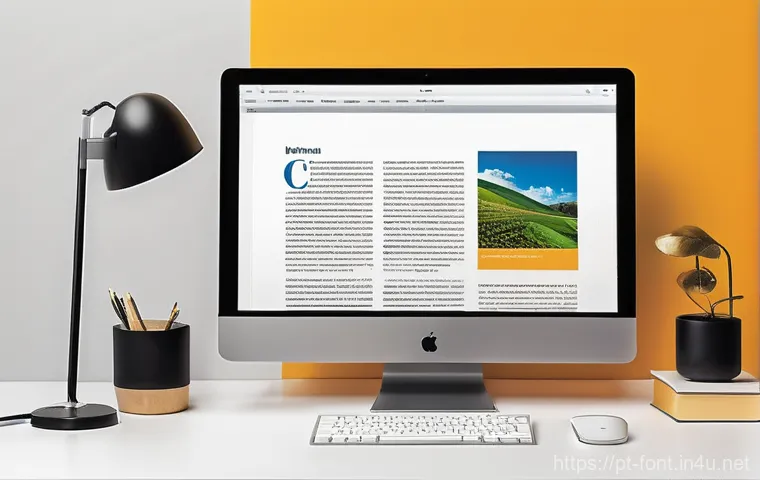
Olá, pessoal! Eu sei que o mundo das apresentações pode ser um desafio e muitas vezes focamos tanto no conteúdo que acabamos esquecendo de um detalhe que faz TODA a diferença: a escolha da fonte e o seu tamanho.
Juro pra vocês, já vi apresentações geniais perderem completamente a força porque a mensagem se perdia em meio a textos ilegíveis ou a um design que mais confundia do que ajudava.
Não é só uma questão de “bonito” ou “feio”, gente; estamos falando de impacto, de profissionalismo e, principalmente, de garantir que sua ideia brilhe de verdade!
Nesta era digital, onde reuniões online se tornaram a norma e a atenção das pessoas é um recurso valiosíssimo, o que funciona bem em um auditório lotado talvez não seja o ideal para quem está assistindo no celular ou no tablet.
As tendências de design e as ferramentas de inteligência artificial estão sempre evoluindo, mas o bom senso tipográfico continua sendo a base para prender o público.
Afinal, a primeira impressão e a legibilidade contínua são cruciais para manter sua audiência engajada do início ao fim. Querem evitar aqueles olhares confusos e ter apresentações que realmente convertem e impressionam, deixando a sua marca por onde passam?
Vamos mergulhar fundo e desvendar todos os segredos para escolher a fonte perfeita!
A Psicologia das Fontes: Mais Que Estilo, Emoção e Percepção
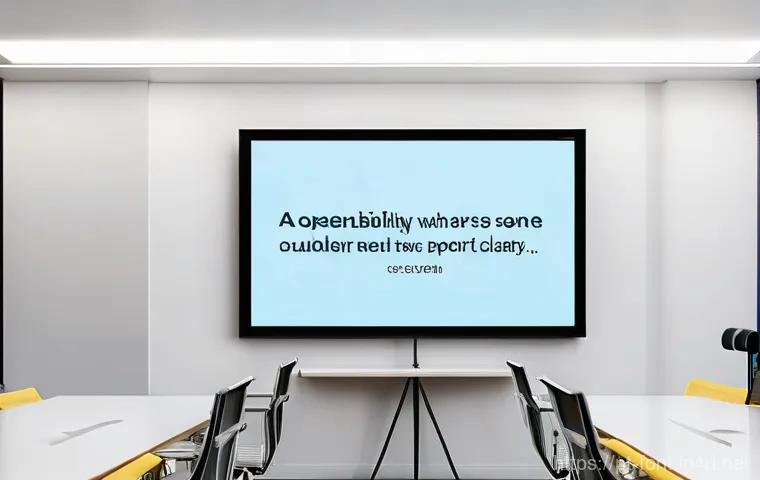
Como a Escolha da Fonte Afeta a Audiência
Sabe aquela sensação quando você vê um logotipo ou um texto e ele simplesmente “passa a mensagem” sem você nem precisar ler com atenção? É a psicologia das fontes agindo!
Acreditem, cada tipo de letra evoca uma emoção diferente, uma percepção particular. Uma fonte mais arredondada pode transmitir amigabilidade e acessibilidade, perfeita para um workshop criativo.
Já uma fonte mais serifada e clássica pode gritar “autoridade” e “tradição”, ideal para uma apresentação acadêmica ou corporativa séria. Eu mesma já testei e comprovei: em um evento sobre inovação, usei uma fonte mais moderna e limpa e a reação do público foi visivelmente mais engajada, sentindo que o conteúdo era realmente de ponta.
Se eu tivesse usado uma fonte super formal, talvez a mensagem de vanguarda não tivesse sido tão bem absorvida. É como escolher a roupa certa para a ocasião, a fonte precisa estar em sintonia com o seu discurso e com quem está do outro lado.
Pensar nisso me ajudou a transformar slides “ok” em apresentações verdadeiramente memoráveis.
Transmitindo Credibilidade e Profissionalismo
A verdade é que a credibilidade começa antes mesmo de você abrir a boca. Ela começa no visual. Uma fonte mal escolhida, que parece infantil para um tema sério, ou que é difícil de ler, pode, infelizmente, minar toda a sua autoridade.
Eu já caí nessa armadilha no início da minha carreira, usando fontes “divertidas” demais em apresentações que exigiam seriedade, e a percepção dos meus superiores não foi das melhores.
Aprendizado doloroso, mas valioso! Hoje, entendo que a fonte é uma extensão da sua voz. Ela precisa reforçar o profissionalismo e a seriedade da sua mensagem, se for o caso.
Por exemplo, fontes como Montserrat ou Lato são escolhas seguras para o ambiente corporativo, transmitindo clareza e um toque moderno sem perder a formalidade.
É sobre construir confiança visualmente, e uma tipografia bem pensada faz exatamente isso. Se você quer que as pessoas levem sua apresentação a sério, comece pela base: a escolha da fonte certa que comunica respeito pelo seu conteúdo e pela sua audiência.
Tamanho É Documento? A Importância do Tamanho da Fonte para Apresentações Impecáveis
Adequando o Tamanho para Diferentes Ambientes
A grande questão do tamanho da fonte é que não existe uma regra única que sirva para todas as situações. Minha experiência me mostrou que o que funciona em uma sala de reuniões pequena, com poucas pessoas sentadas próximas à tela, é um desastre em um auditório gigante, onde a última fileira mal consegue ver o que está escrito.
O público online então, com cada um assistindo no seu próprio dispositivo – seja um monitor grande ou um celular minúsculo –, exige uma atenção ainda maior.
Para apresentações presenciais em grandes espaços, eu sempre recomendo um tamanho mínimo de 30pt para o corpo do texto e 40-50pt para os títulos. Parece grande, eu sei, mas é a garantia de que ninguém vai ficar vesgo tentando ler!
Já para reuniões online, onde as pessoas estão mais perto de suas telas, podemos ser um pouco mais flexíveis, mas nunca menos que 20-24pt para o corpo do texto, para não forçar a vista.
Pensem na experiência do espectador! Eu já sofri muito em palestras com letras miúdas, e prometi a mim mesma que nunca faria isso com a minha audiência.
A Legibilidade Acima de Tudo: Não Force a Visão do Seu Público
Olha, gente, de que adianta ter a ideia mais brilhante do mundo se ninguém consegue ler o que está no seu slide? A legibilidade é a estrela principal aqui, e o tamanho da fonte é seu braço direito.
Ninguém vai ler. Para evitar tudo isso, o meu conselho é: simplifique. Use fontes de fácil leitura, mantenha o texto conciso – no máximo 6 linhas por slide e umas 6 palavras por linha, se possível.
Teste a sua apresentação em diferentes dispositivos antes de mostrar ao mundo. Pede para um amigo olhar no celular dele. Se ele conseguir ler sem reclamar, você está no caminho certo!
É um toque de carinho com a sua audiência, e isso, gente, faz toda a diferença para o seu profissionalismo e para a mensagem realmente grudar na mente das pessoas.